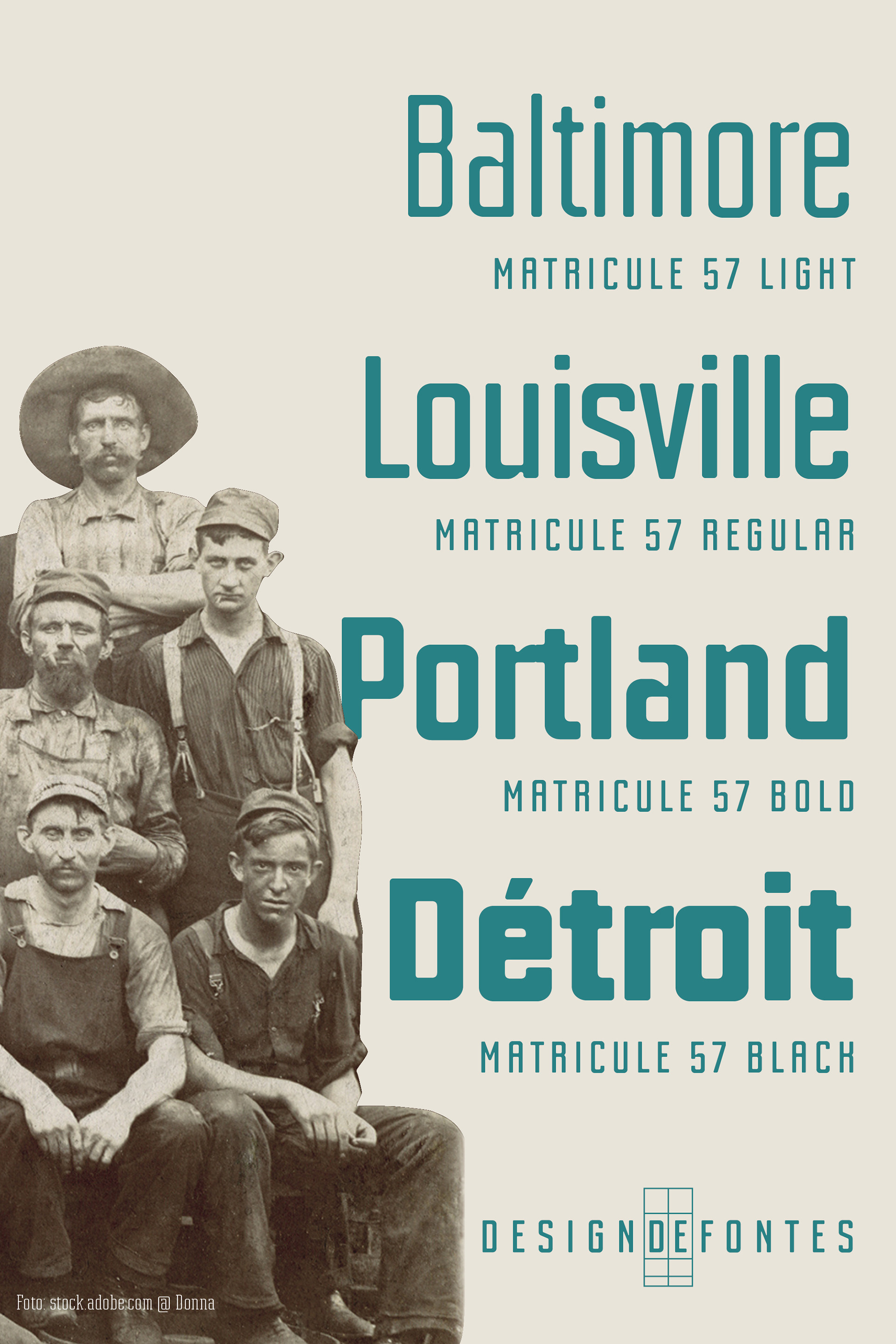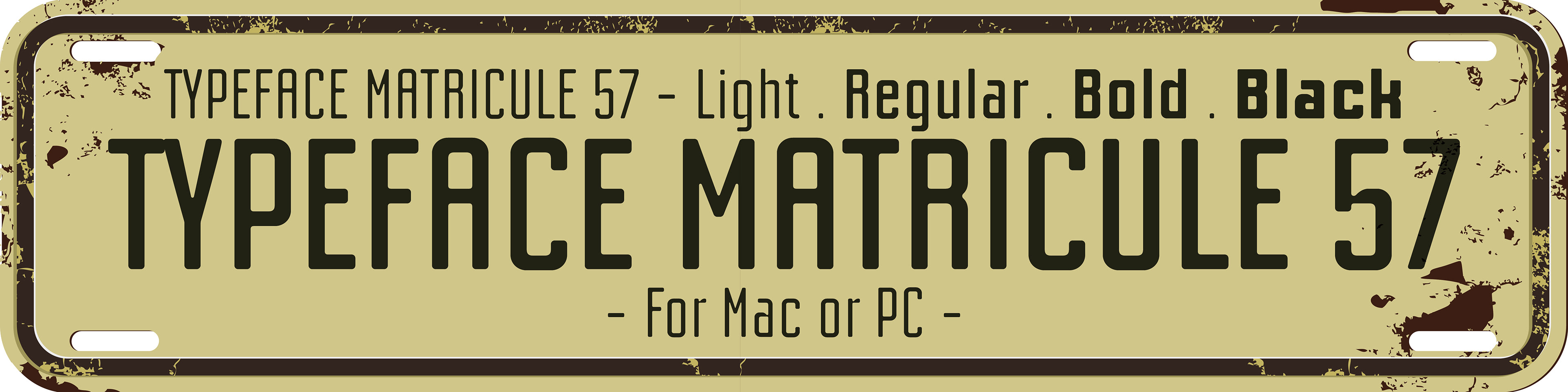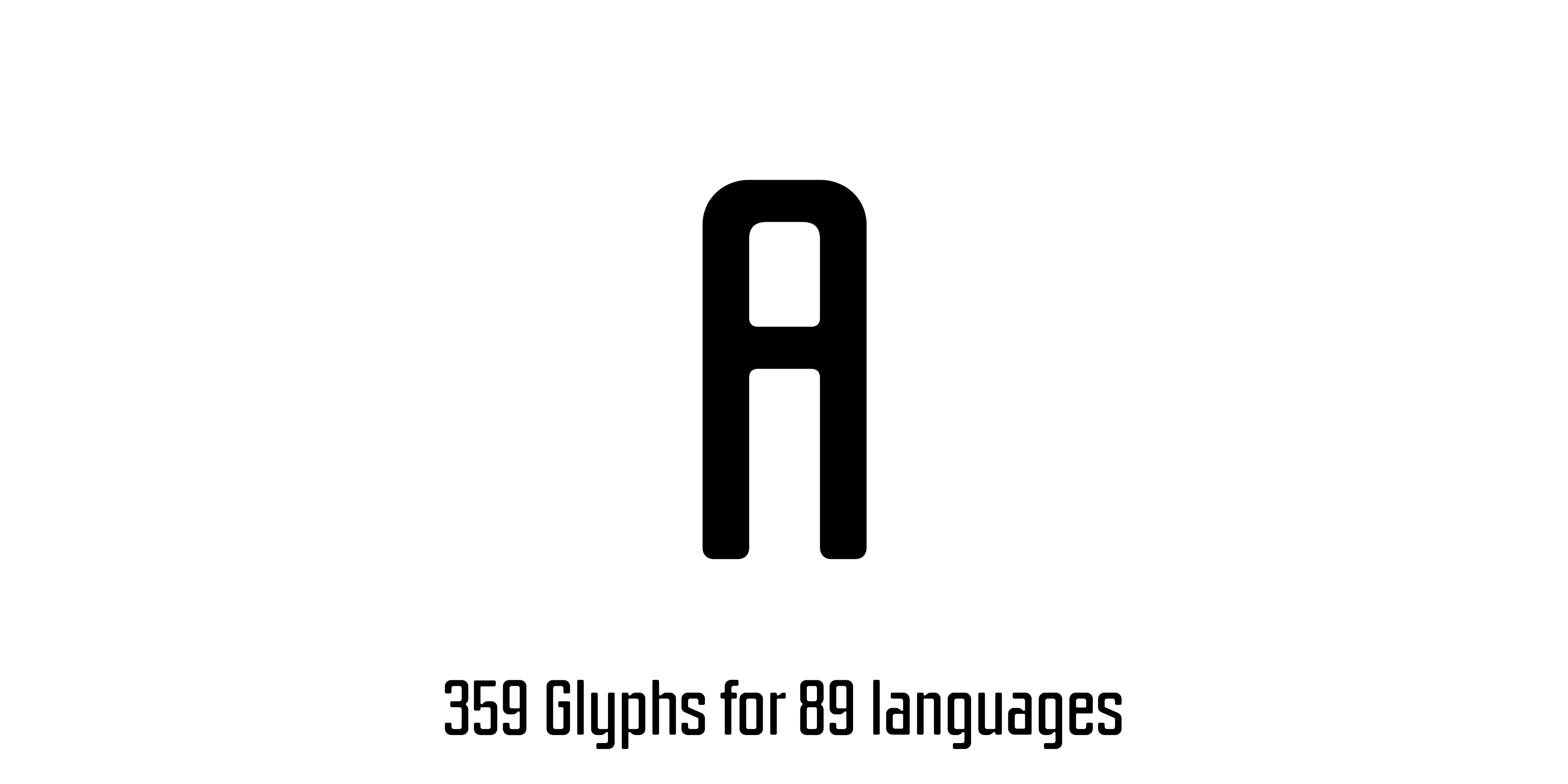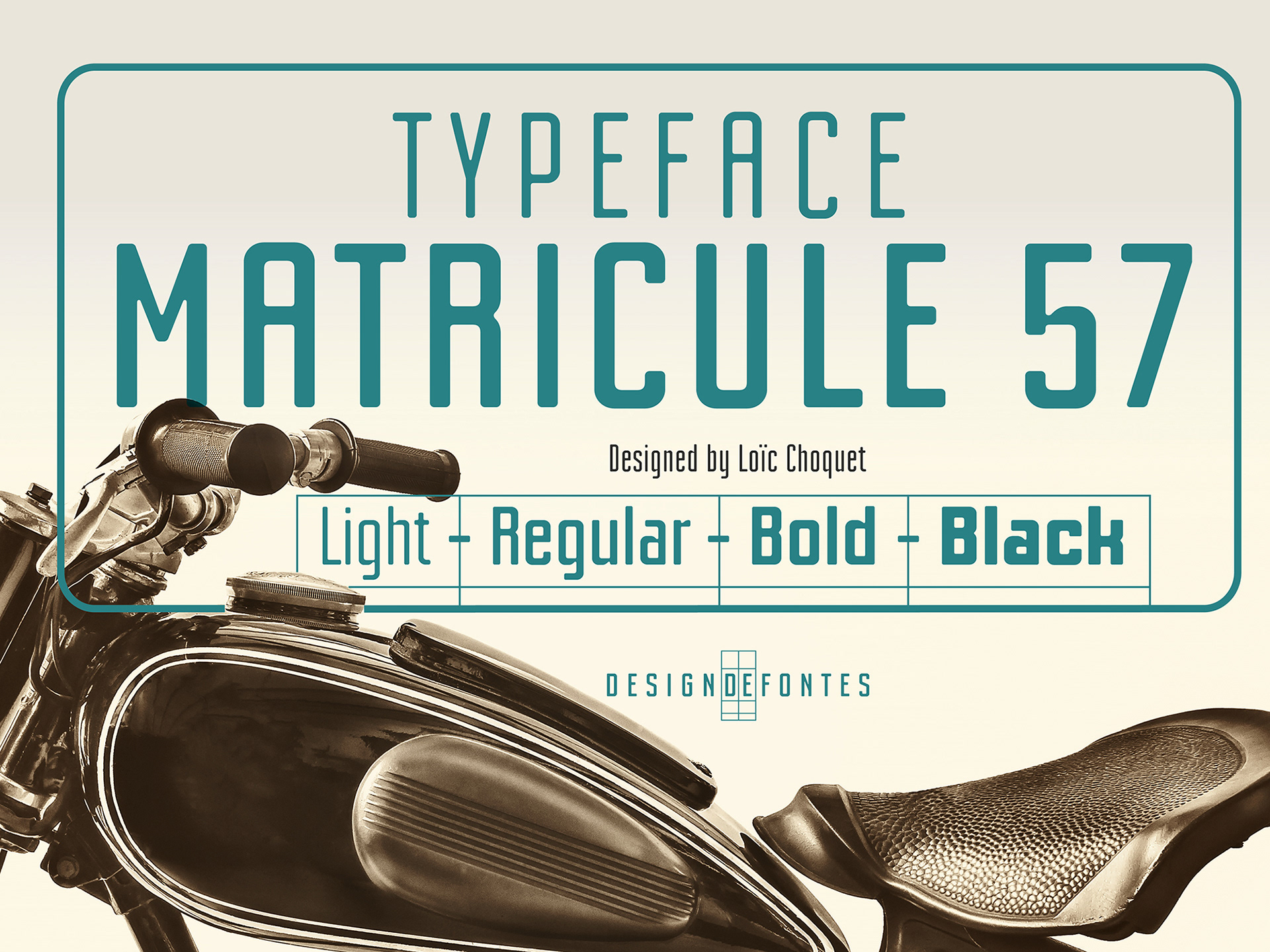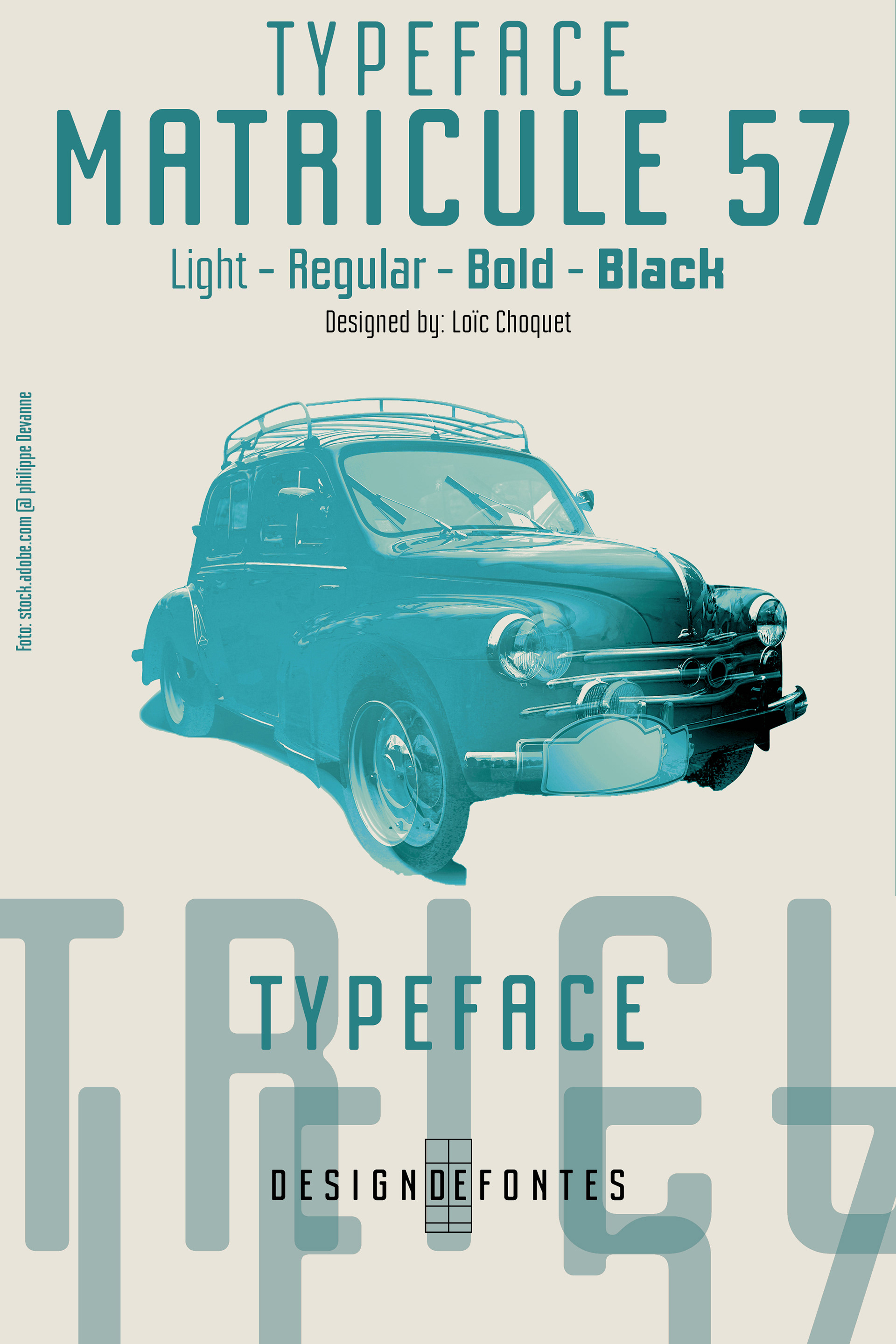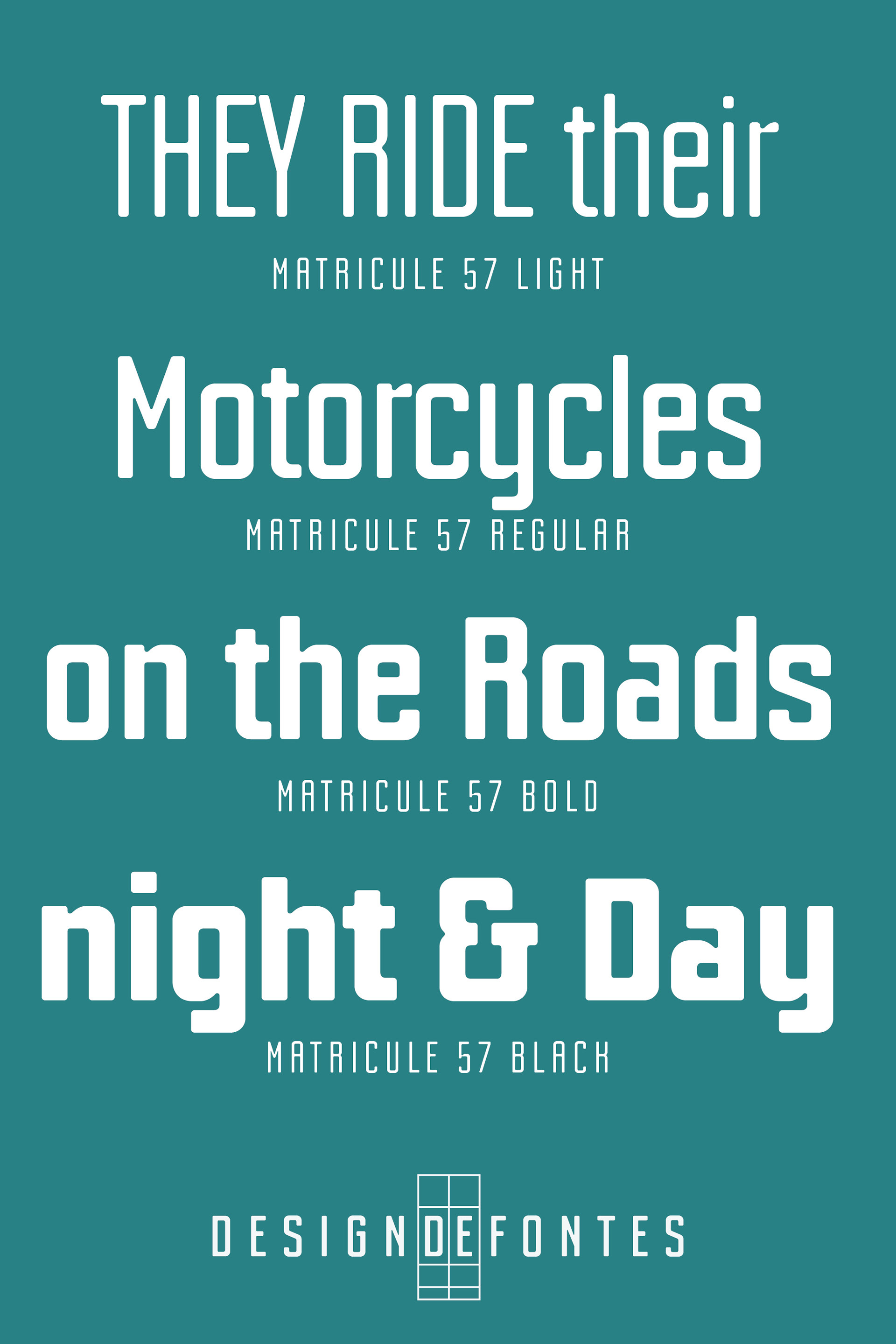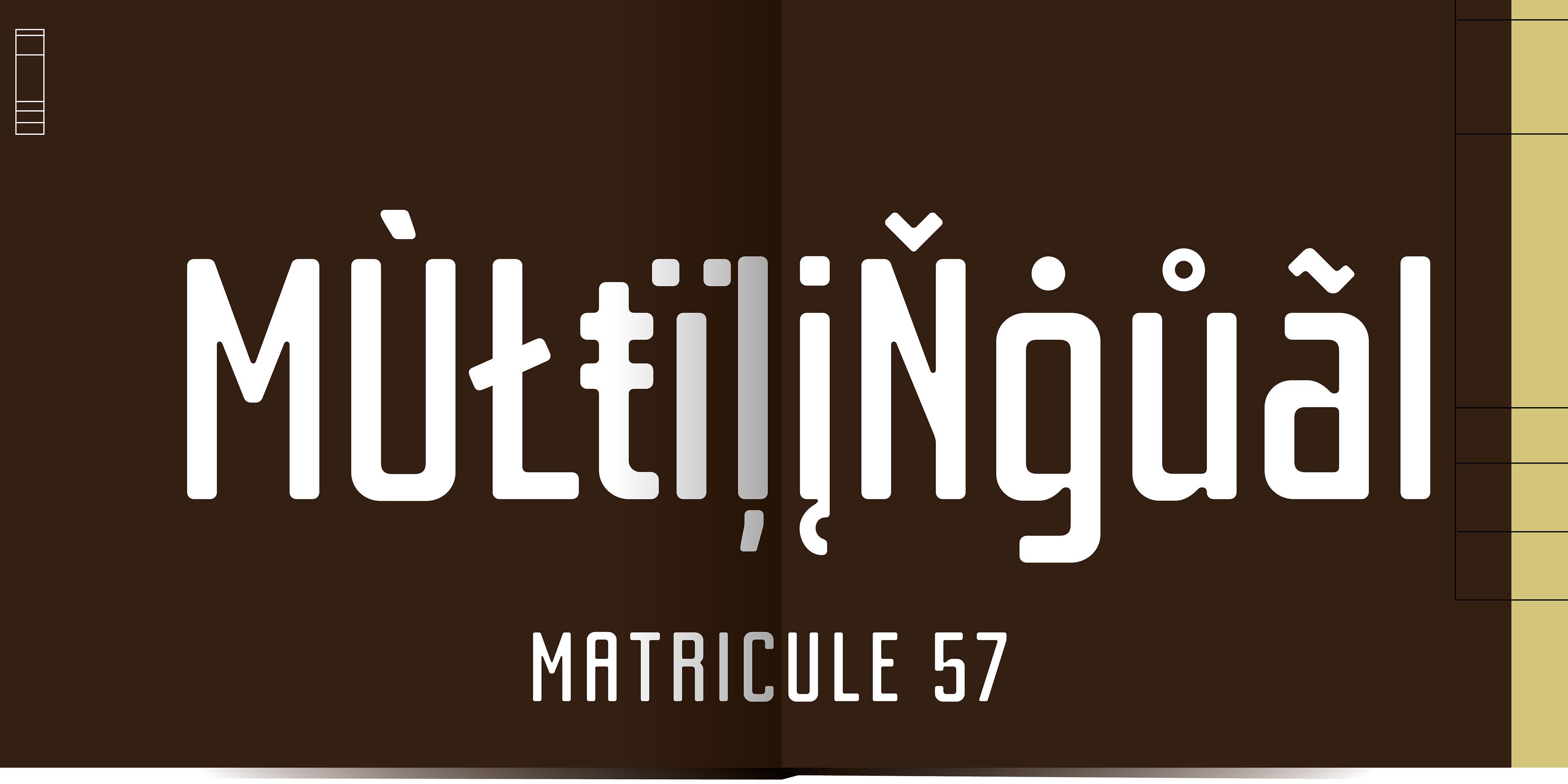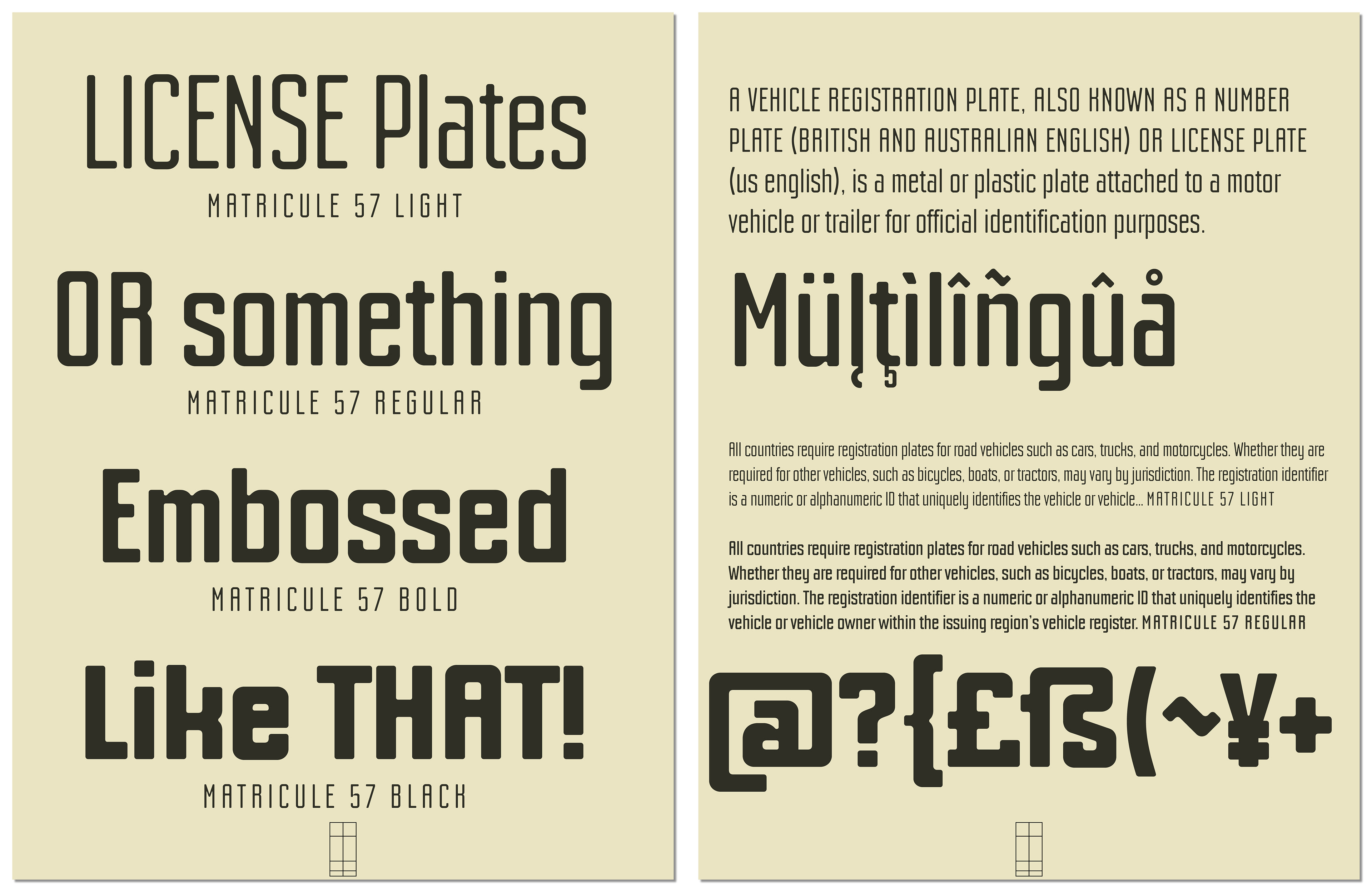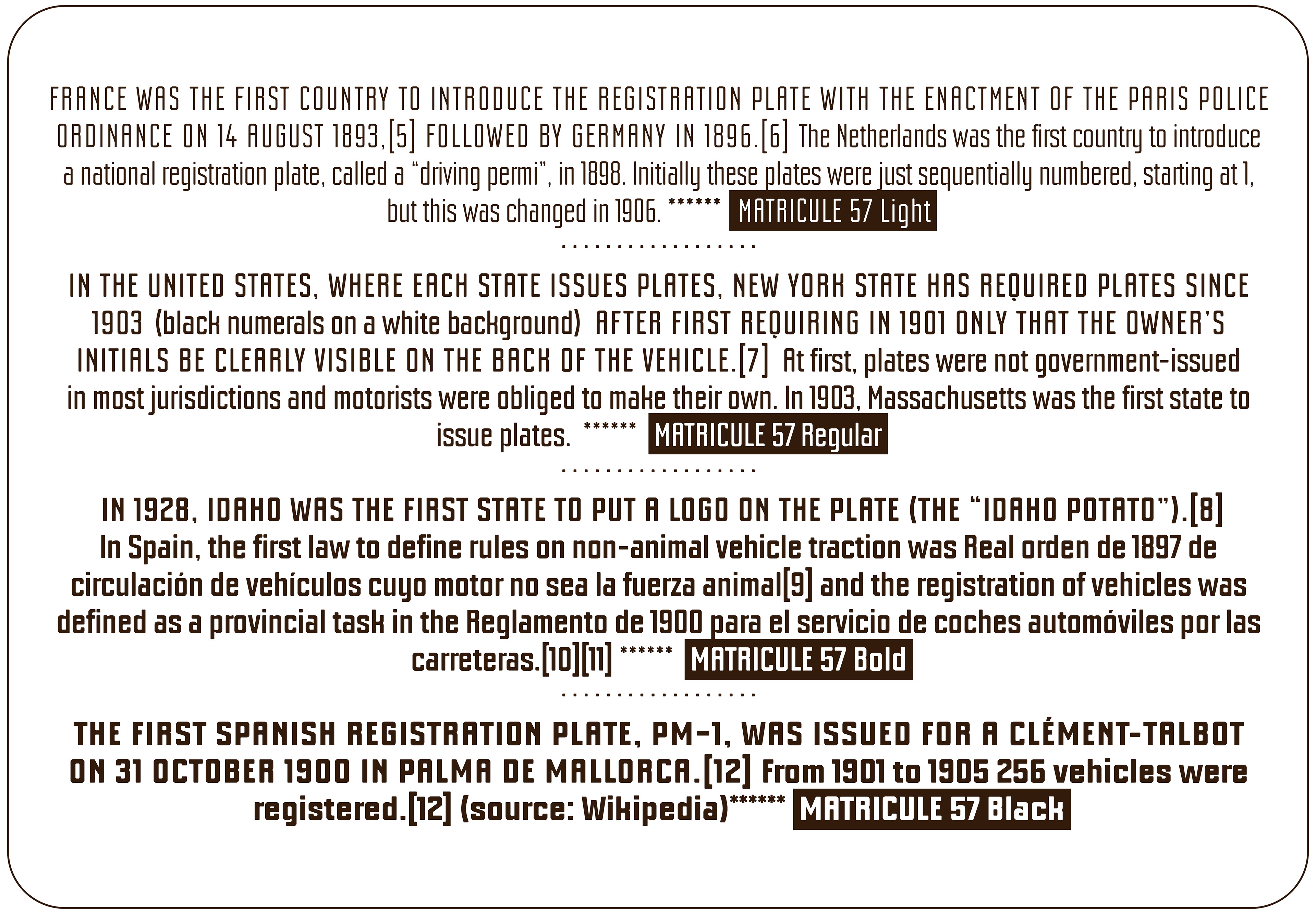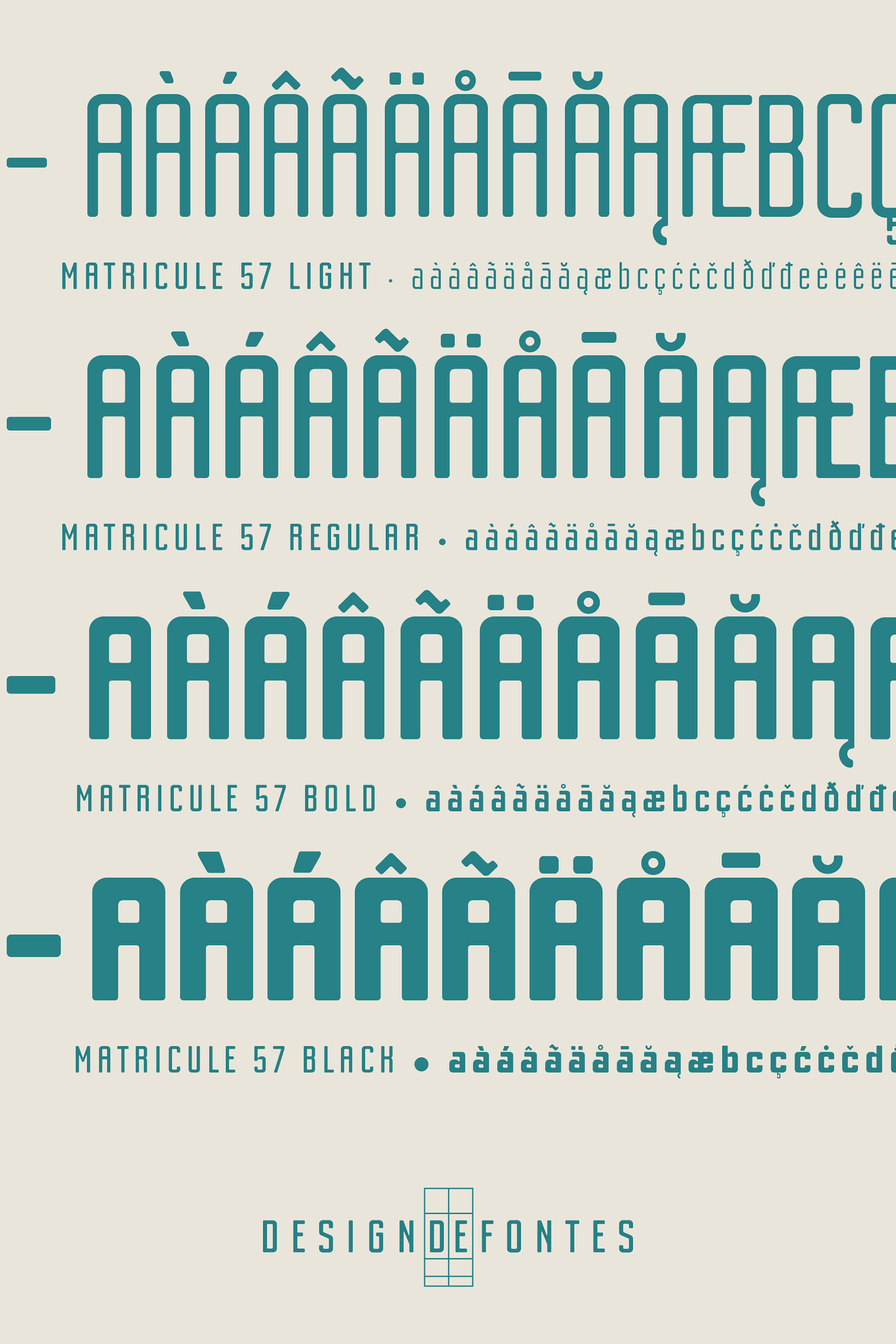
CARACTèRE TYPOGRAPHIQUE MATRICULE 57
SCHRIFT MATRICULE 57
Matricule 57 est une police constituée de 4 fontes. Utilisable pour vos projets éditoriaux, logotypes, affiches, packaging, etc. Chaque fonte contient 359 caractères offrant une large possibilité d’emploi pour des compositions en alphabet latin.
Die Matricule 57 Schriftfamilie besteht aus 4 Schriften. Sie eignet sich hervorragend für Editorial-Projekte, Logotypen, Plakate, Verpackungen und mehr. Die Schrift enthält 359 Glyphen und bietet eine hohe Flexibilität für die Unterstützung lateinischer Sprachen, um sämtlichen typografischen Anforderungen gerecht zu werden
Matricule 57 est un caractère dont le design et inspiré par les plaques d’immatriculations et plus particulièrement par les déformations provoquées par la pression des caractères dans les plaques métalliques. Ces déformations donnent aux caractères un style spécifique notamment concernant les déliés de liaisons de ces caractères.
Matricule 57 est la version condensée de Matricule, un caractère dessiné par Loïc Choquet.
Matricule 57 est composé de 4 fontes : light, regular, bold et black.
Matricule 57 ist eine Schrift, deren Design von Nummernschildern inspiriert ist, insbesondere von den Verformungen, die durch den Druck der Buchstaben auf die Metallplatten entstehen. Diese Verformungen verleihen den Zeichen einen spezifischen Stil, insbesondere in Bezug auf die Übergänge und Verbindungen der Buchstaben.
Matricule 57 ist die schmale Version von Matricule, einer Schrift, die von Loïc Choquet entworfen wurde.
Matricule 57 besteht aus 4 Schriftschnitten: Light, Regular, Bold und Black.
Matricule 57 est prête à l’emploi pour 89 langues différentes
Matricule 57 ist in 89 unterschiedlichen Sprachen nutzbar